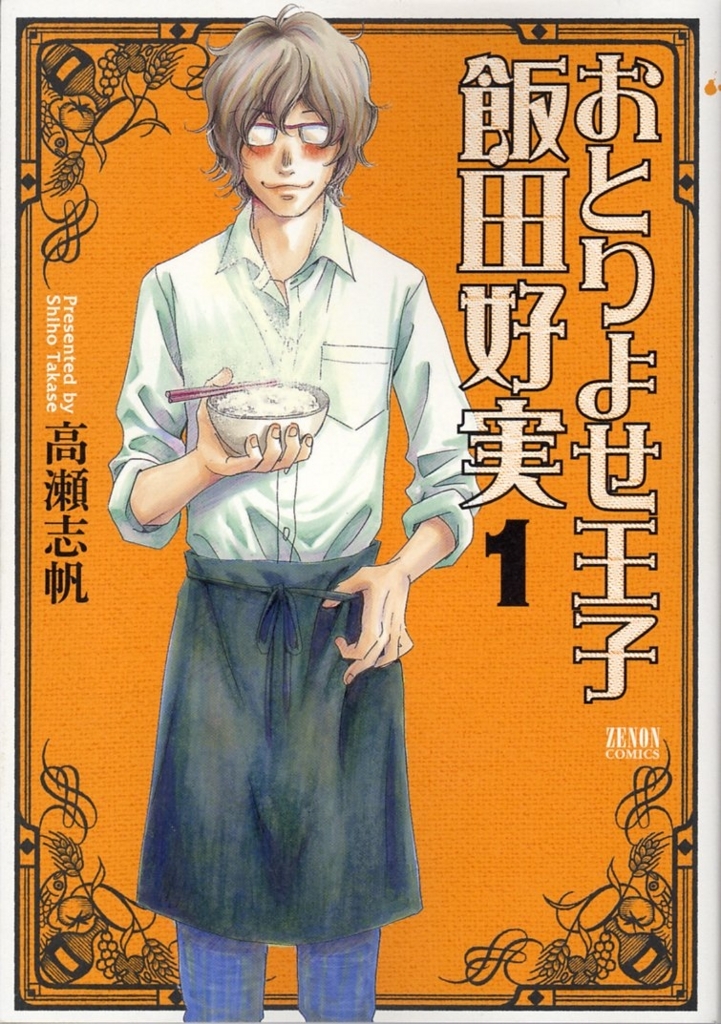
おとりよせ王子
おとりよせ王子は、徳間書店による発行する「月刊コミックゼノン」にて2011年2月号から2016年7月号まで連載された高瀬志帆による漫画。2013年4月から7月までテレビドラマとしても放送された。
「おとりよせ王子」のタイトルはダイナフォントの優雅宋を使用
「おとりよせ王子」のタイトルにダイナフォントの優雅宋が加工されて採用されている。
少女漫画チックな書体・優雅宋
細い横線と太い直線で構成され、ストロークの先端と末端に欧文書体の花文字のような装飾が施されているのが特徴的な書体。古典的な洋風感があり、ロゴ・POP・タイトル・キャッチコピー・看板等、様々な場面で活用されている。